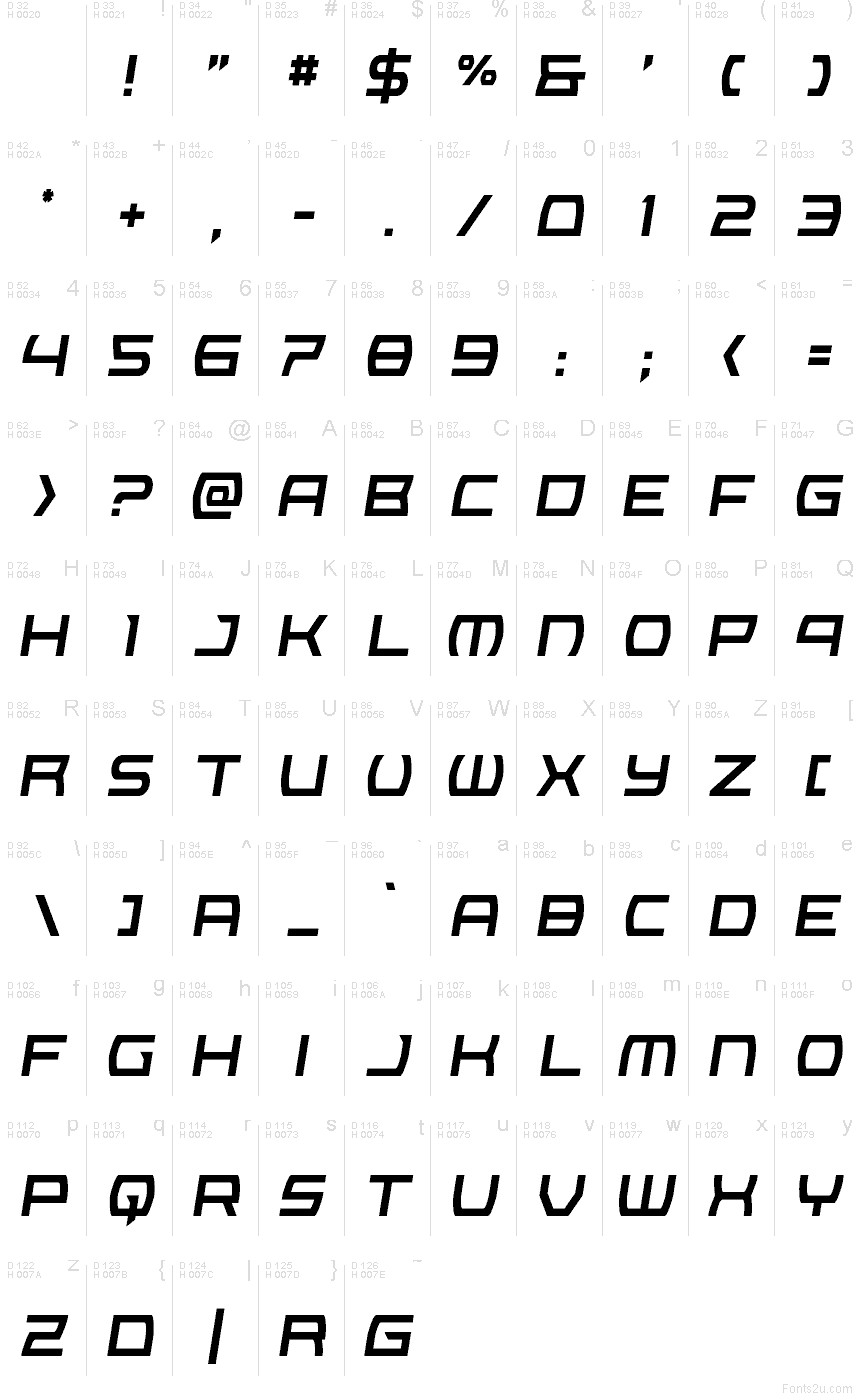
Icemaster Condensed Semi-Ital
Icemaster Condensed Semi-Ital von Iconian Fonts ist eine futuristische Display-Schriftart, die durch ihren rasanten, messerscharfen Schnitt besticht. Die Buchstaben wirken wie aus glatten Paneelen geschnitten, mit schmalen Proportionen, kantigen Kurven und einer dynamischen Vorwärtsneigung. Das verleiht Großbuchstaben den Look eines Sci-Fi-Titels statt eines generischen Techno-Stils.
Diese kostenlose Schriftart eignet sich perfekt für Gaming-Logos, Esports-Branding, Filmplakate, Album-Cover und Titelsequenzen, bei denen kompakte Zeilen Bewegung brauchen. Sie funktioniert auch hervorragend für kurze Überschriften und Monogramme, da die kondensierten, angewinkelten Buchstaben eine dichte, mechanische Silhouette bilden.